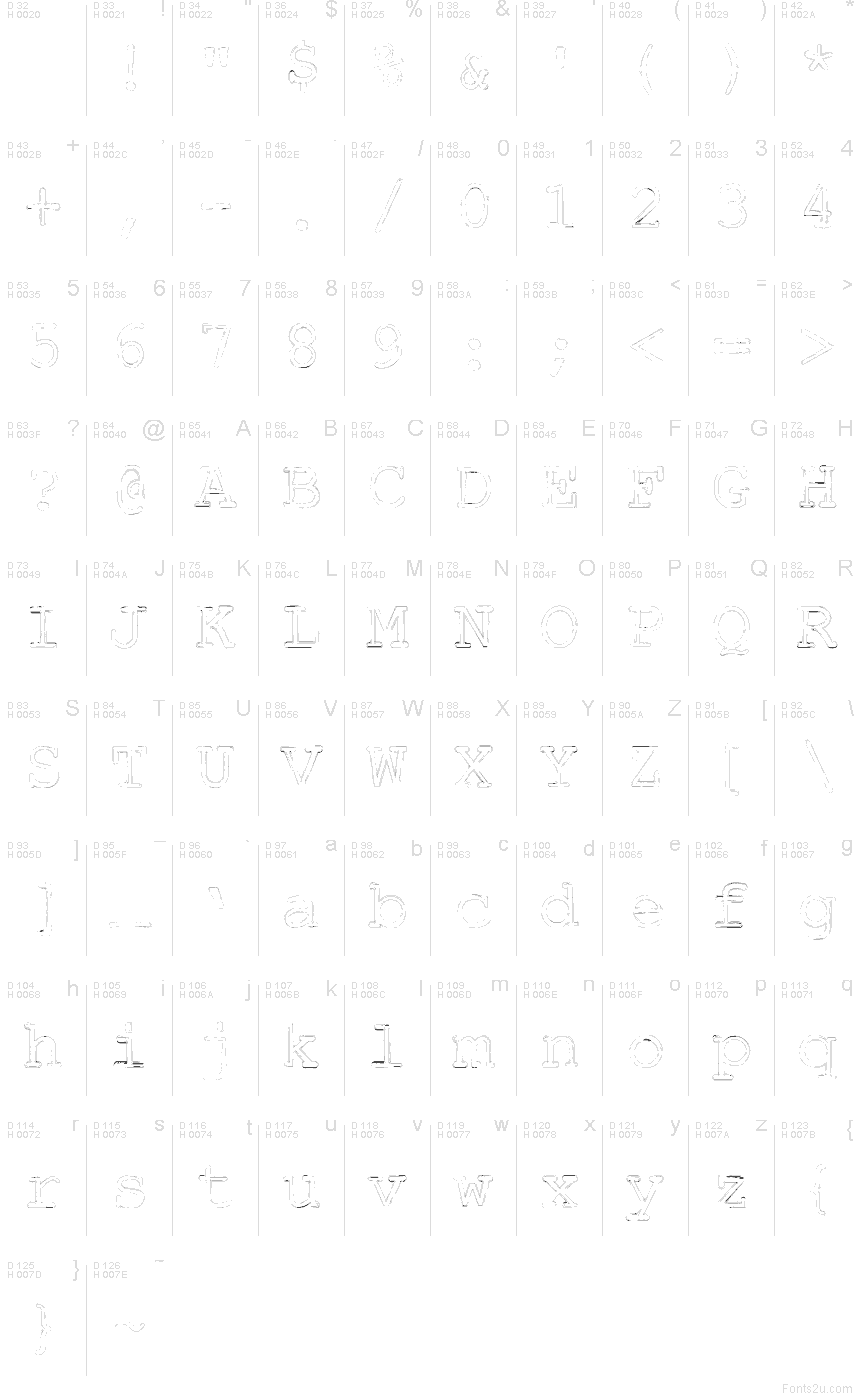
Typewriter Inked Outline od Creativetacos je bezplatné konturované písmo typu display, inspirované vzhledem psacích strojů, s lehce drsným, ručně kresleným obrysem. Otevřené tvary písmen a skicované dvojité linie mu dodávají efekt otisku na papíře, což působí mnohem zajímavěji než běžná digitální úprava.
Typewriter Inked Outline skvěle funguje v titulcích plakátů, redakčních citátech, etiketách, řemeslném brandingu a papírenském zboží, protože konturované provedení udržuje písmena vzdušná, zatímco klasický tvar psacího stroje jim dodává stabilitu. Toto bezplatné písmo se také hodí pro loga, pozvánky a nadpisy v sekcích, pokud chcete text, který vypadá jako kreslený, a ne jen vytištěný.